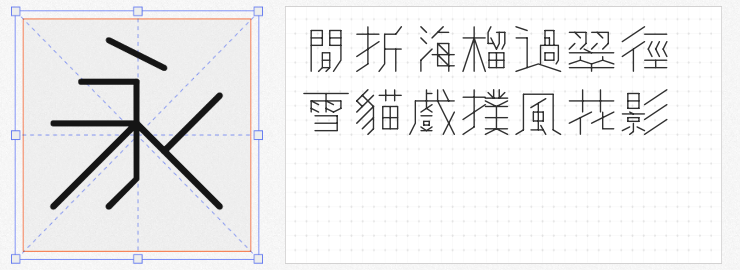
在设计的创意宇宙中,字体是构建独特视觉语言的关键元素。今天,就为大家推荐四款免费商用的创意字体,为你的设计注入别样魅力。
猫啃网故障黑,灵感源自日本的瀞之故障黑体,基于思源黑体精心魔改而成。这款字体浑身散发着浓郁的赛博朋克风格,科幻感十足。其独特的故障风效果,仿佛将人带入一个充满未来科技与数字混乱交织的世界。无论是艺术设计、平面宣传设计,还是网页设计、海报设计,它都能轻松驾驭,为作品增添炫酷的视觉冲击力,瞬间抓住观众的眼球。
猫啃网故障宋与思源宋体 CN 版本覆盖范围一致,继承了思源字体字数丰富的优点,让设计师们无需再为缺字少字而烦恼。它同样采用程序自动处理生成,虽然某些字形可能存在细微不足,但并不影响其整体魅力。这款字体在保持故障风格的同时,又融入了宋体的优雅,为设计带来别样的韵味,是设计打工人不可或缺的实用之选。
字玩哥特黑白无常,免费且超黑。它汲取哥特艺术风格中的阴森、诡异、恐怖之感,在字型中巧妙加入不规则血滴元素,营造出强烈的游戏恐怖氛围和紧张感。在游戏海报、恐怖主题活动宣传等设计中,这款字体能够瞬间将观众带入一个充满神秘与恐惧的世界,增强作品的感染力和吸引力。
黄令东细线体是一款十分特别的字体,由程序自动生成,采用递归根式包装语言编写。其语法灵感源于标记语言和传统书法练习的“米”网格,赋予了字体独特的艺术气质。值得注意的是,它是繁体词根,输入简体字会自动映射成繁体字形。这种独特的繁体韵味,为设计增添了一份古典与优雅,适合用于文化、艺术等主题的设计作品。
这四款免费商用的创意字体,各具特色,能为你的设计带来无限可能。不妨大胆尝试,让它们在你的作品中绽放光彩!